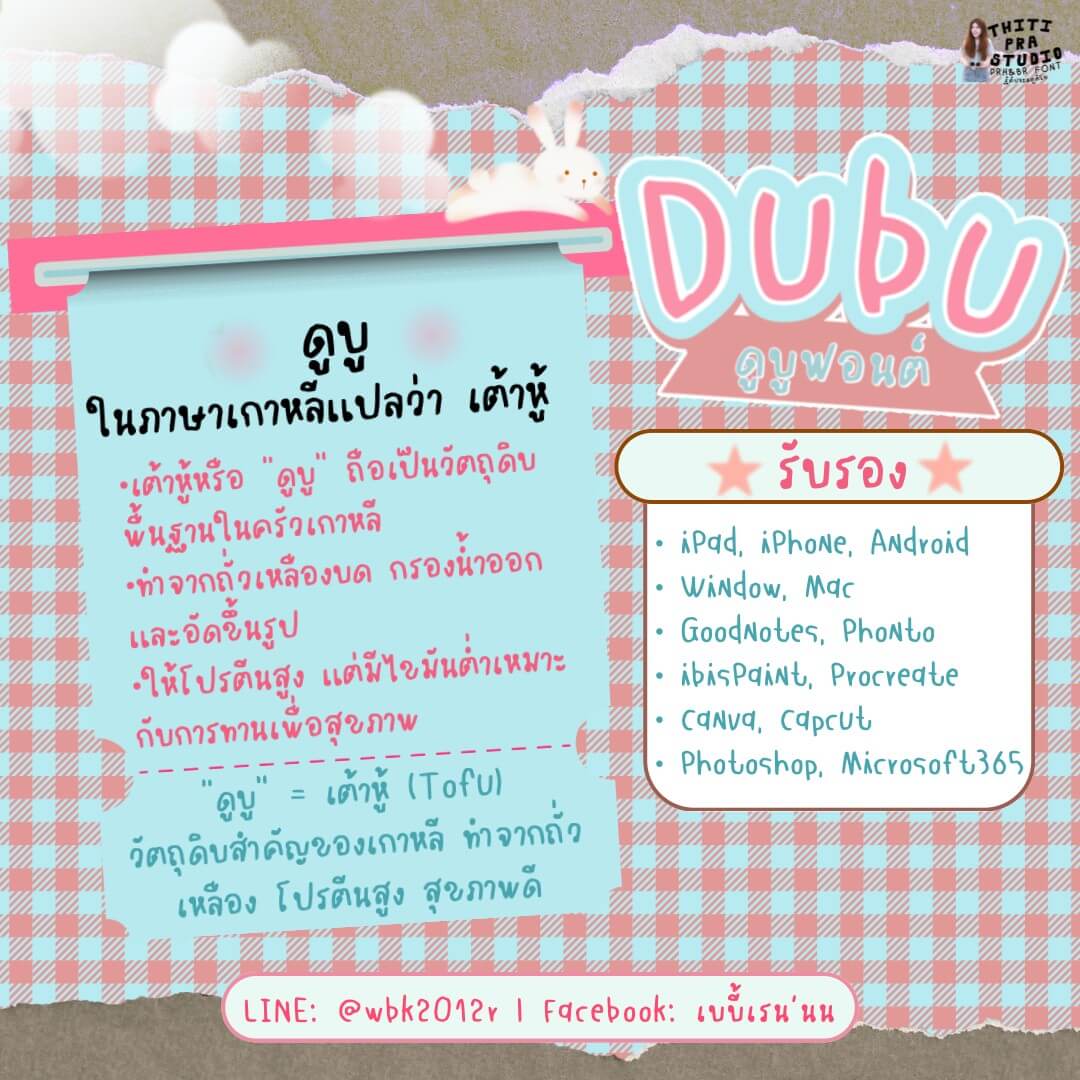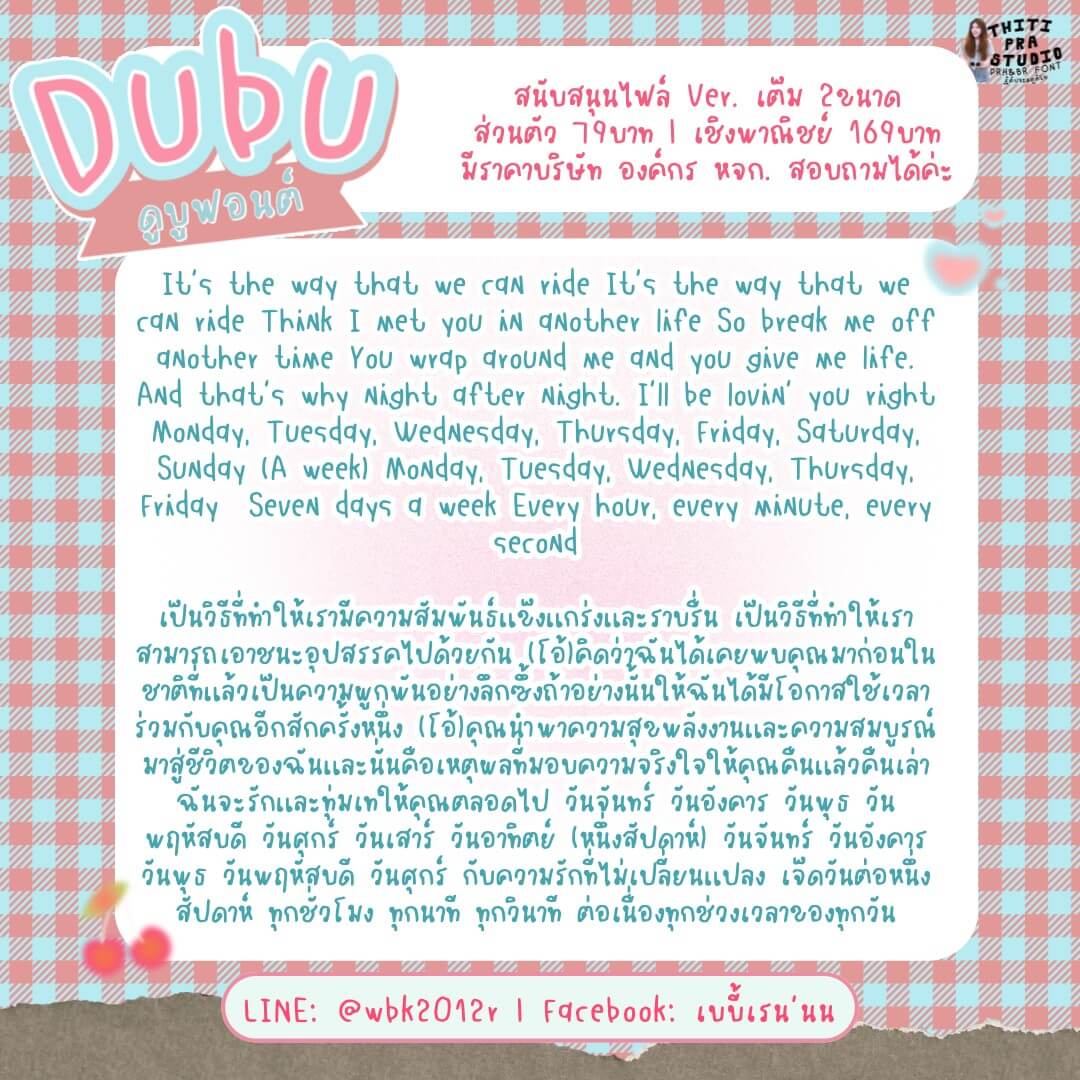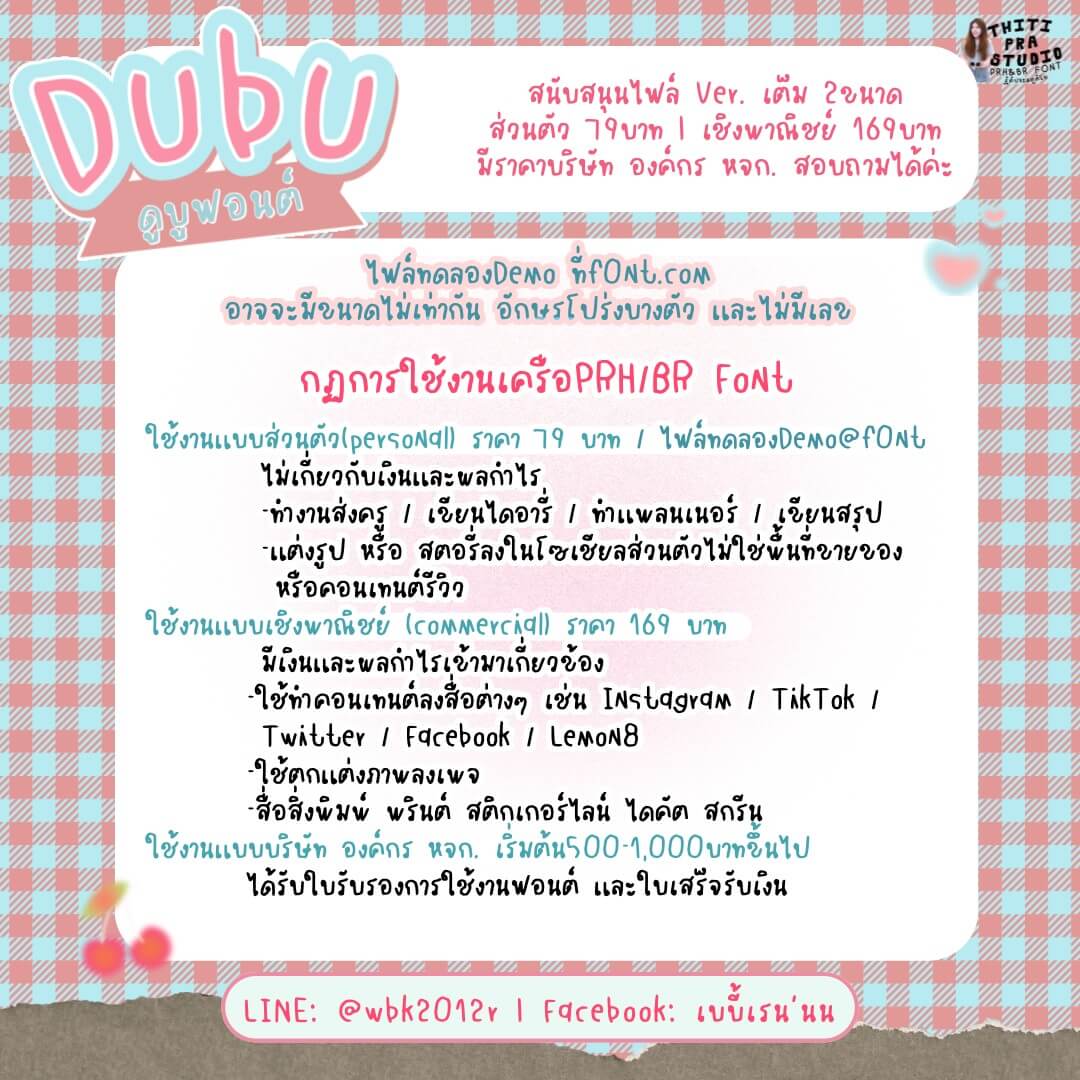
ดูบู (PRHDubu)
PRHDubu Font / ดูบูฟอนต์ – ฟอนต์แนวลายมือเด็กมีลูกเล่นยุกยิก น่ารักสดใส ให้ฟีลแบบไม่ทางการ
• ฟอนต์มีขนาดไม่เท่ากัน / ไม่มีเลข/วรรณยุกต์ / อักษรโปร่งบางตัว